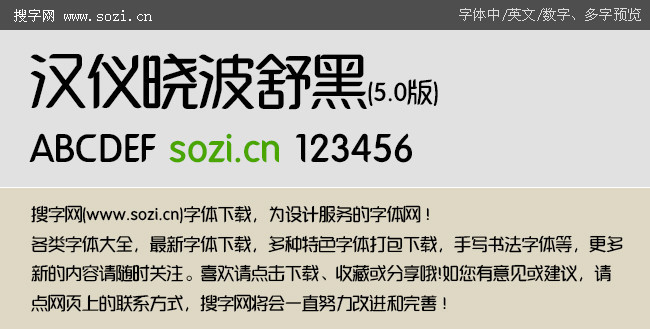
漢儀曉波舒黑5.0
搜字網(wǎng)提供一款漢儀曉波舒黑5.0字體下載,漢儀曉波舒黑是一款漂亮的藝術(shù)字體。由漢儀曉波工作室出品,漢儀曉波舒黑本身字骨偏硬,橫豎撇捺均為直線,所以我們嘗試了在筆畫細(xì)節(jié)上以圓角修飾,使字體的形式表達(dá)更加溫和,適用于各類女性化電商主題的應(yīng)用。(本字體為個(gè)人非商用版,如需要商用請(qǐng)聯(lián)系漢儀公司購買版權(quán))